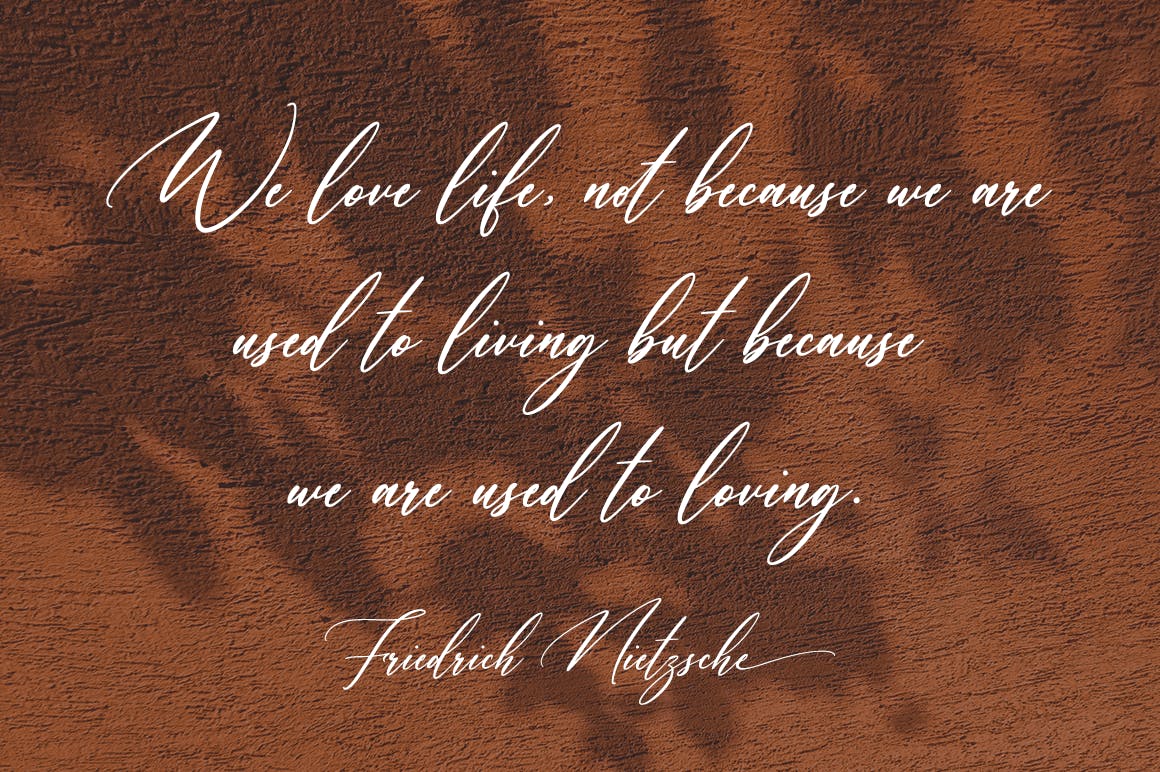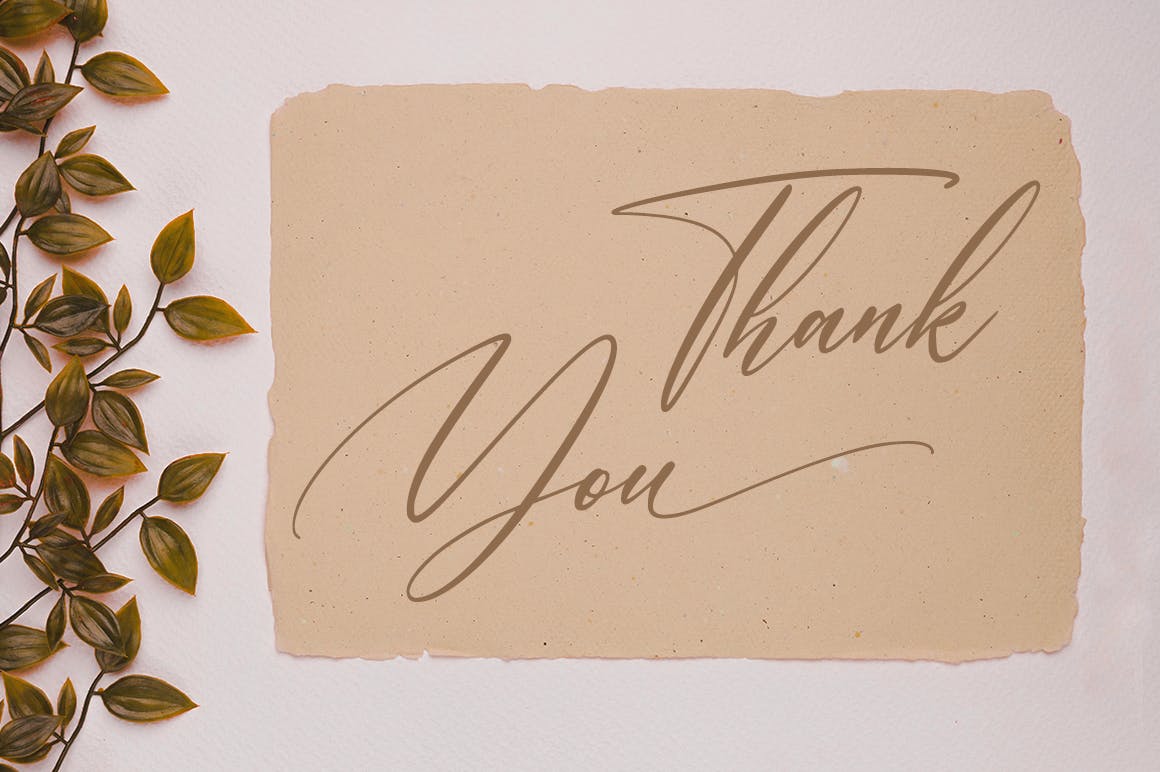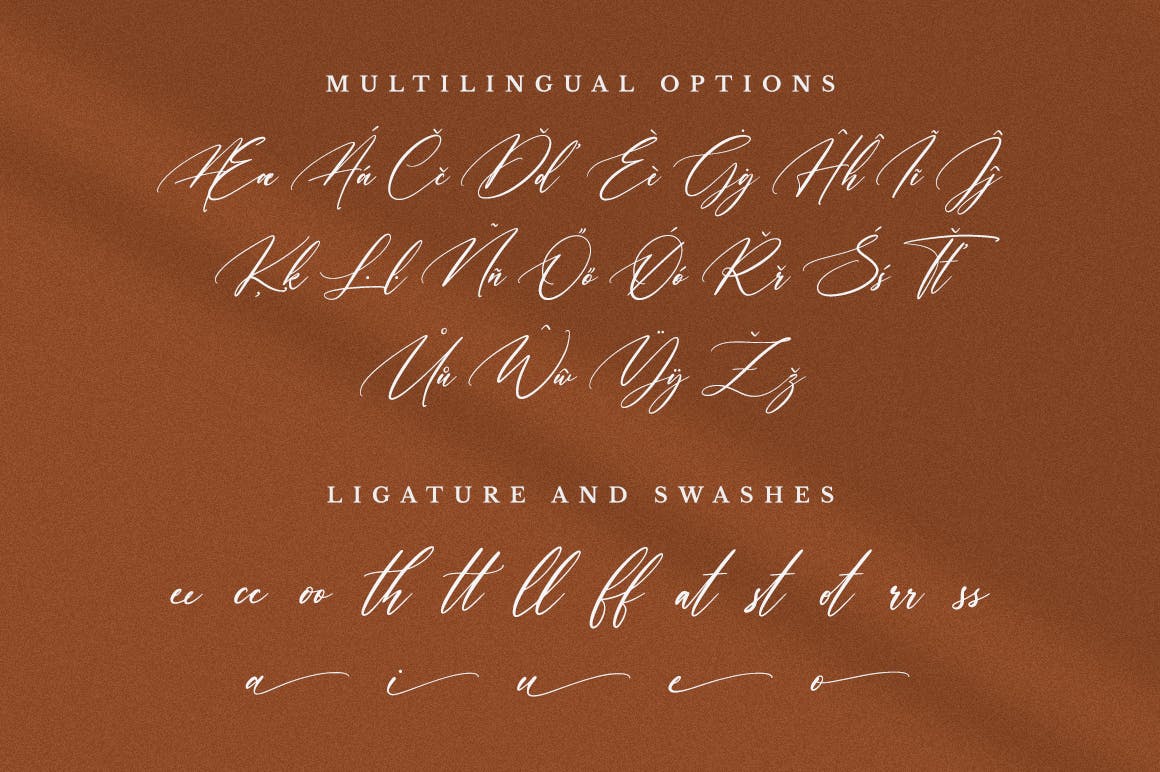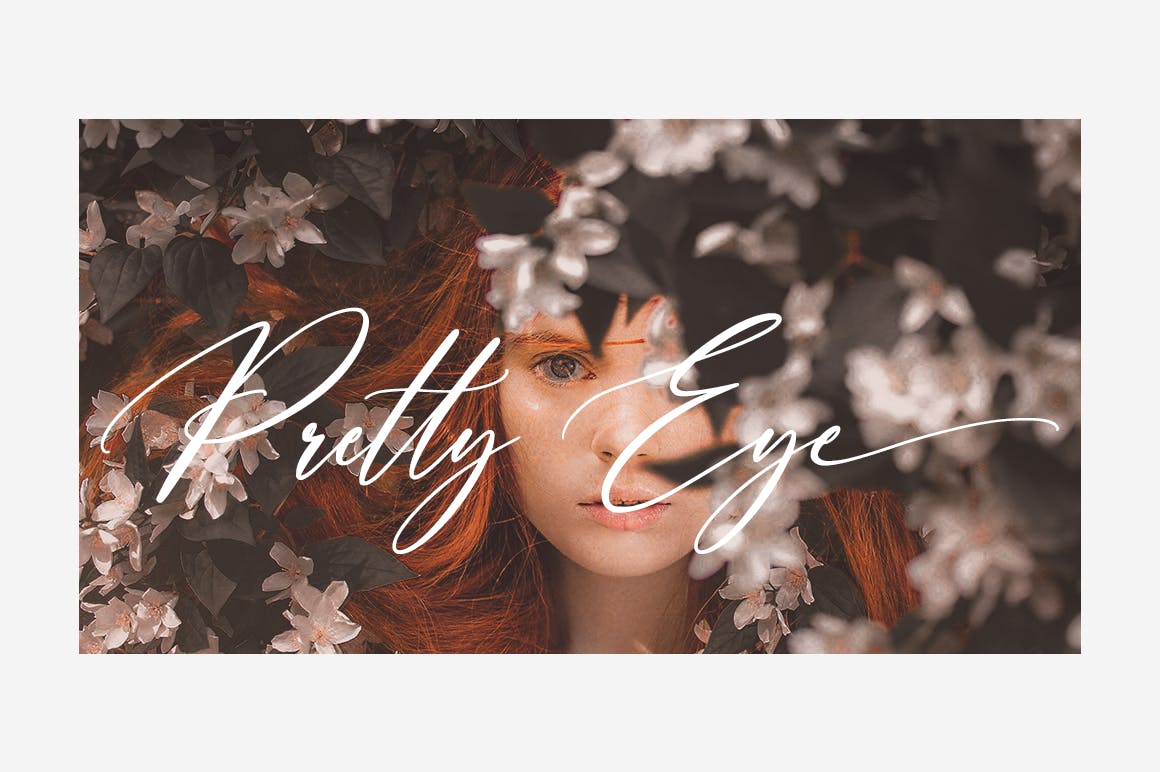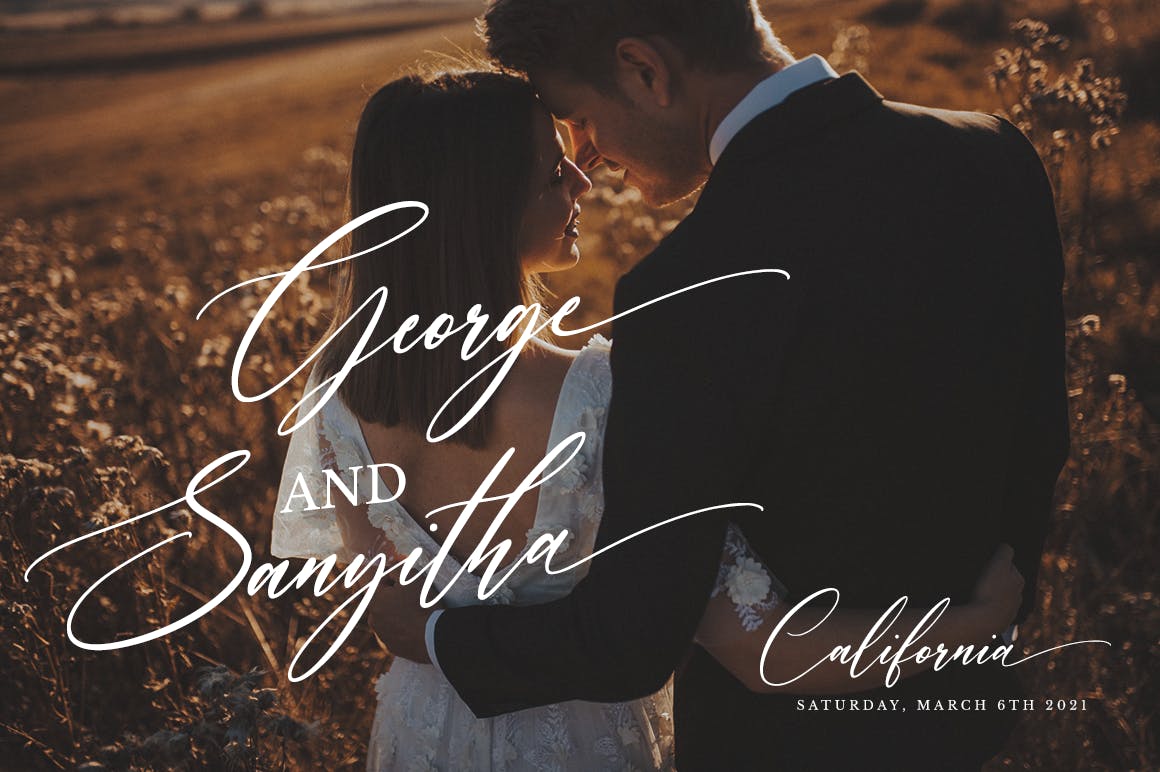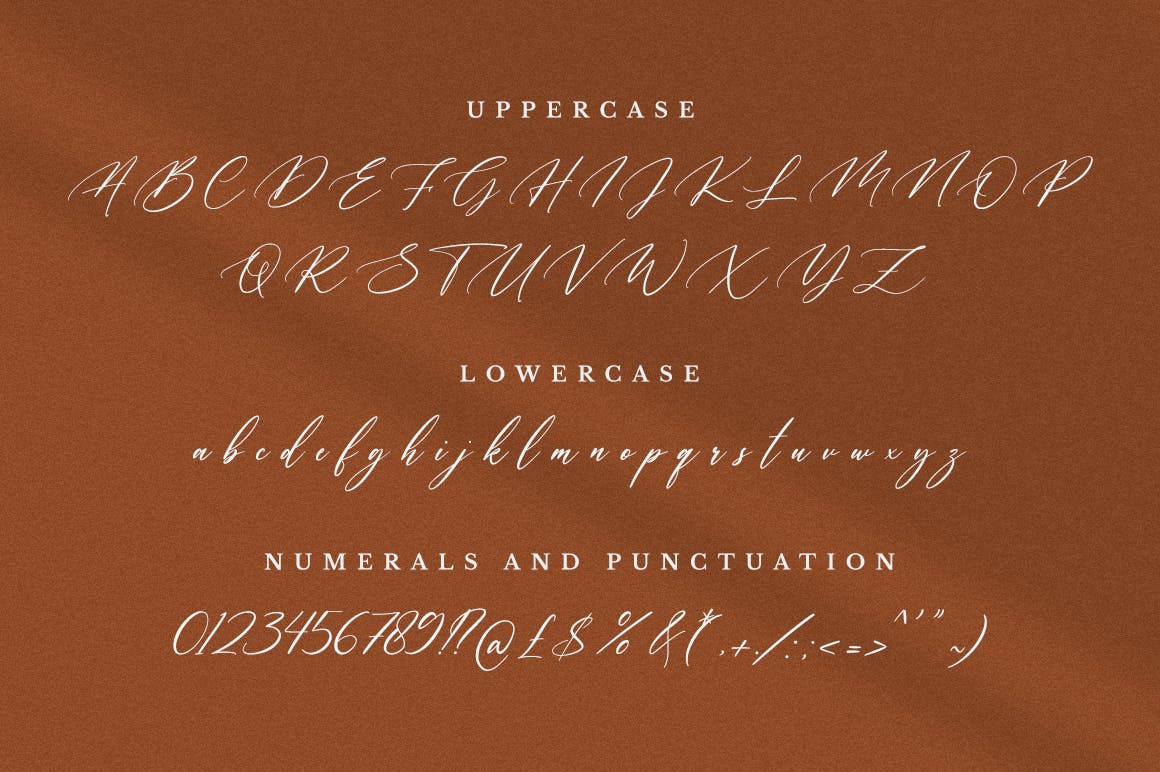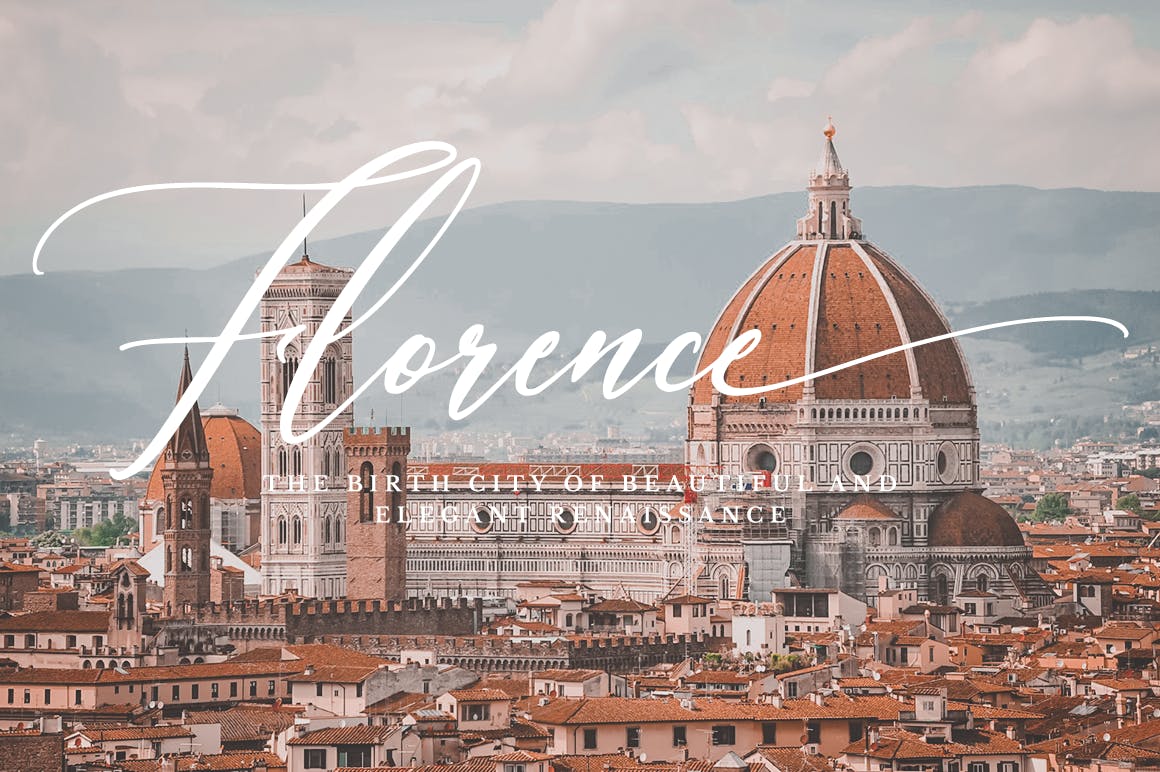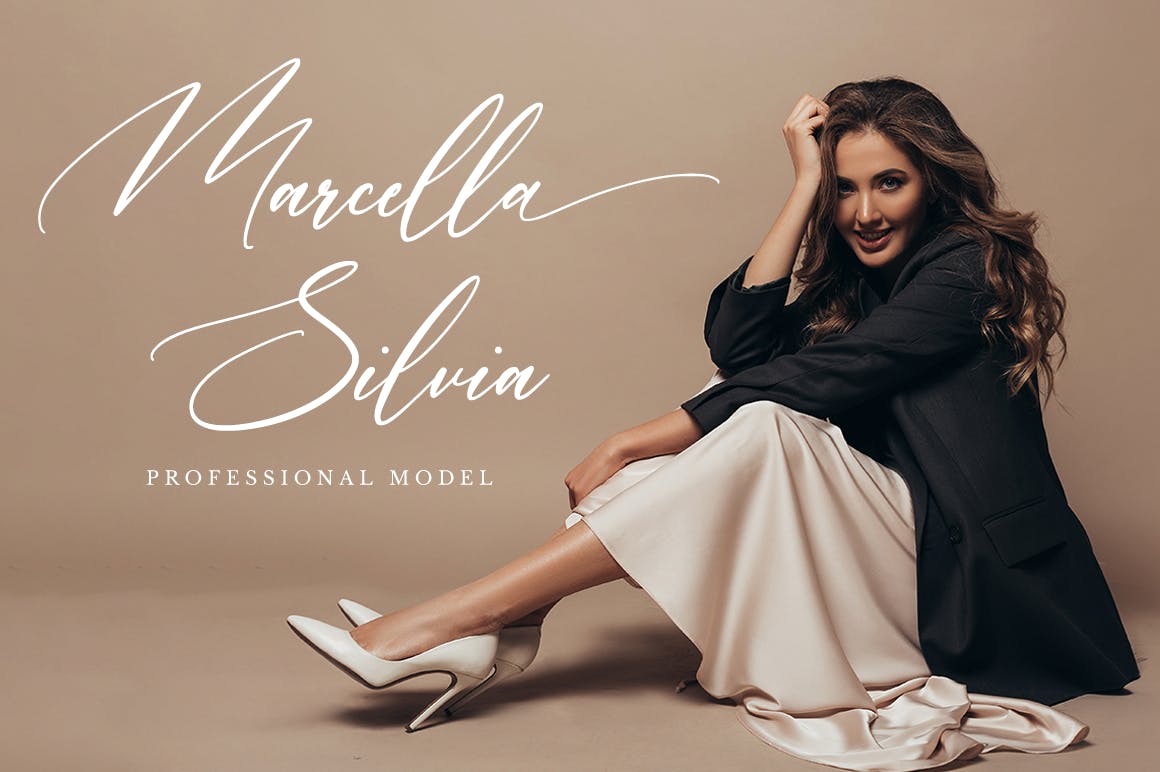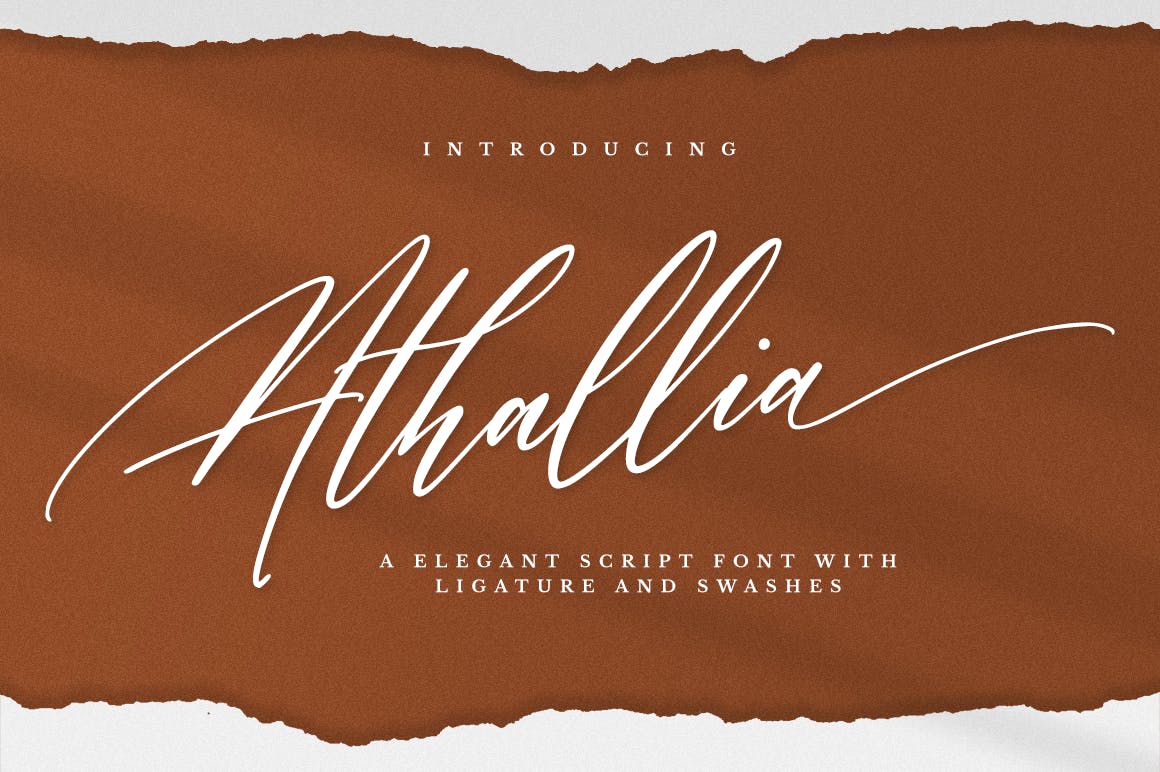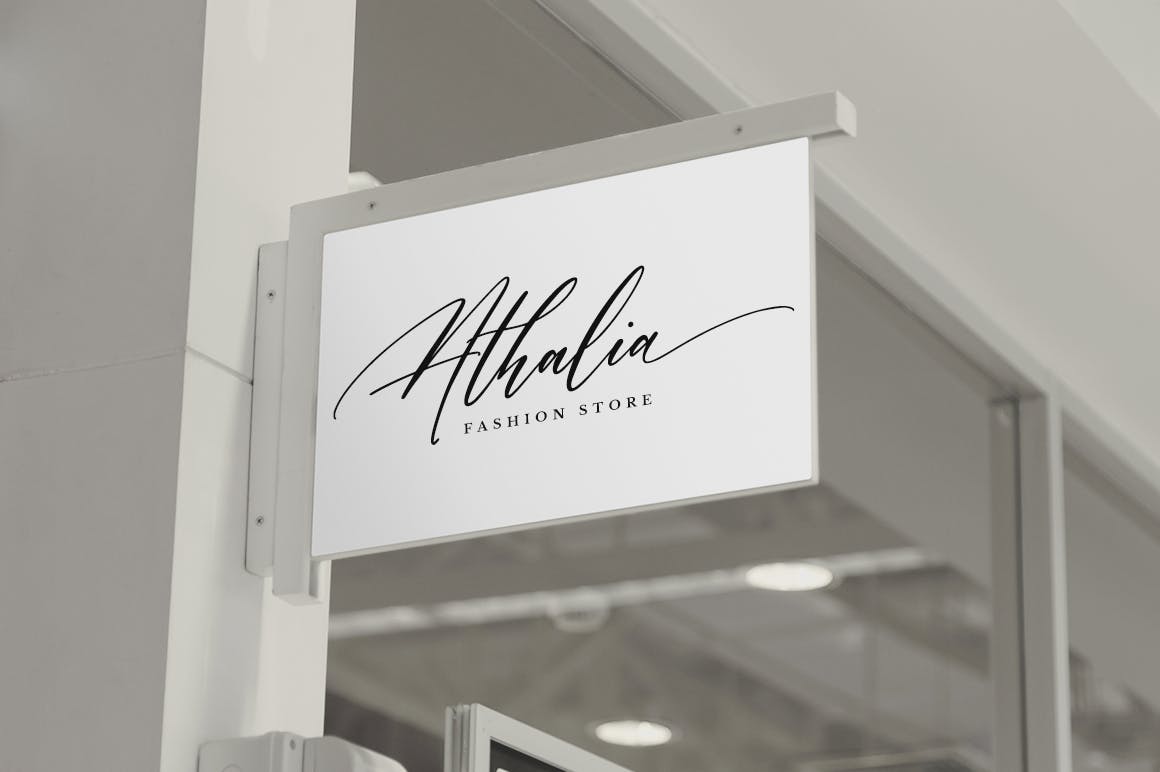
فونت Athallia یک فونت خوشخط و جذاب است. این فونت با الگوهای زیبا و جایگزینهای شگفتانگیز ترکیبی از خوشنویسی کاپرپلیت و سبکهای دستنویس است. طراحی آن برای انتقال ظرافت و زیبایی، با سبکی جذاب، نرم، تمیز و زنانه ایجاد شده است.